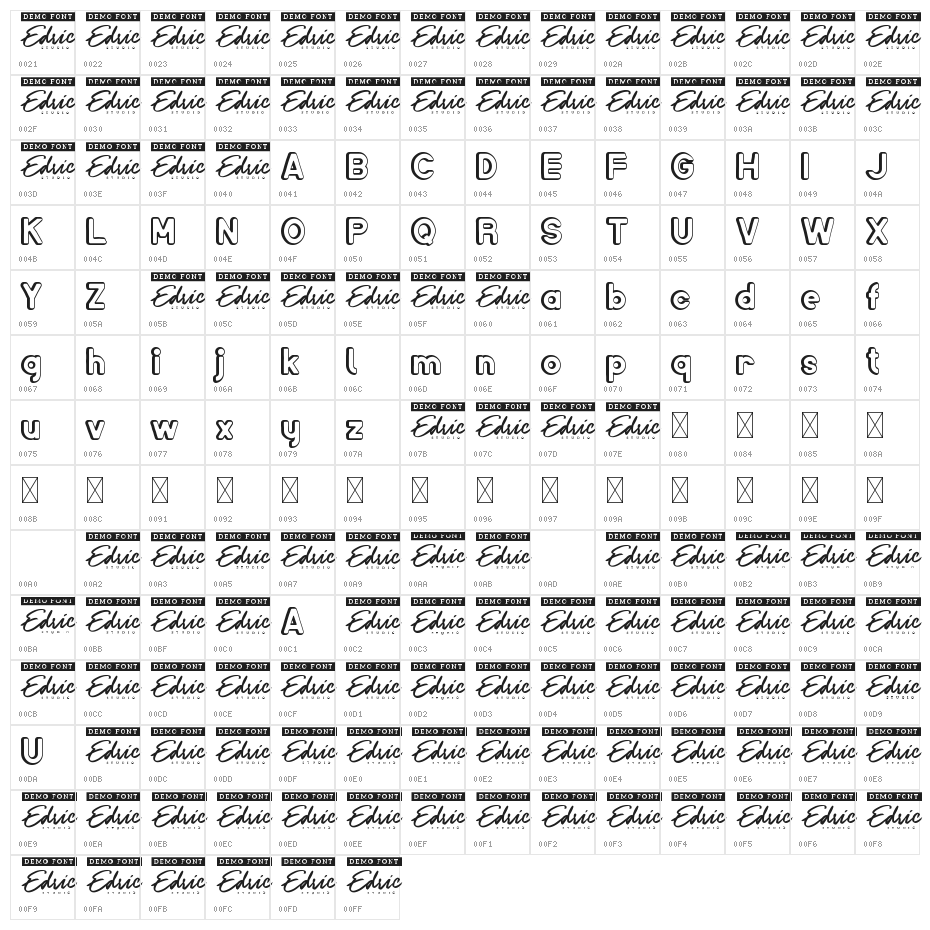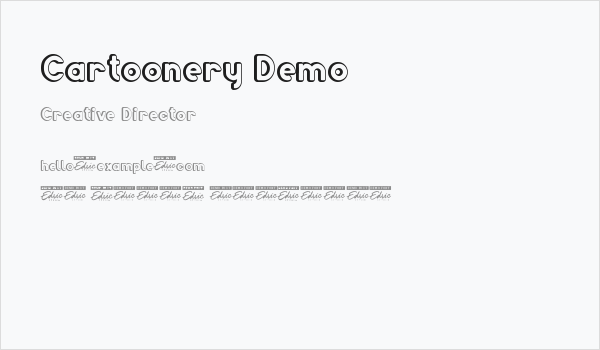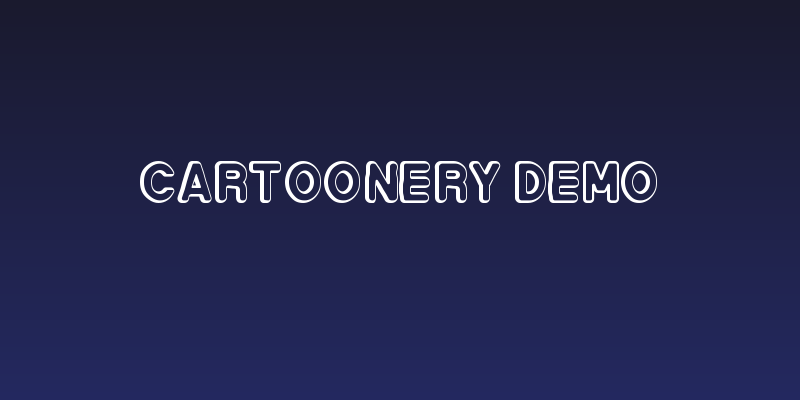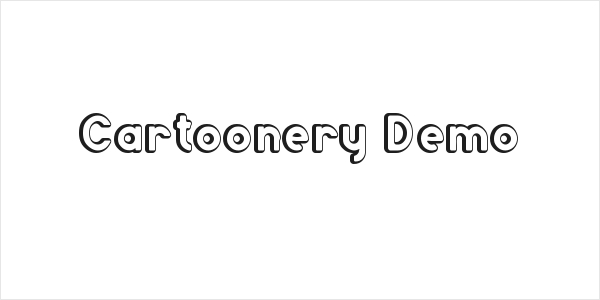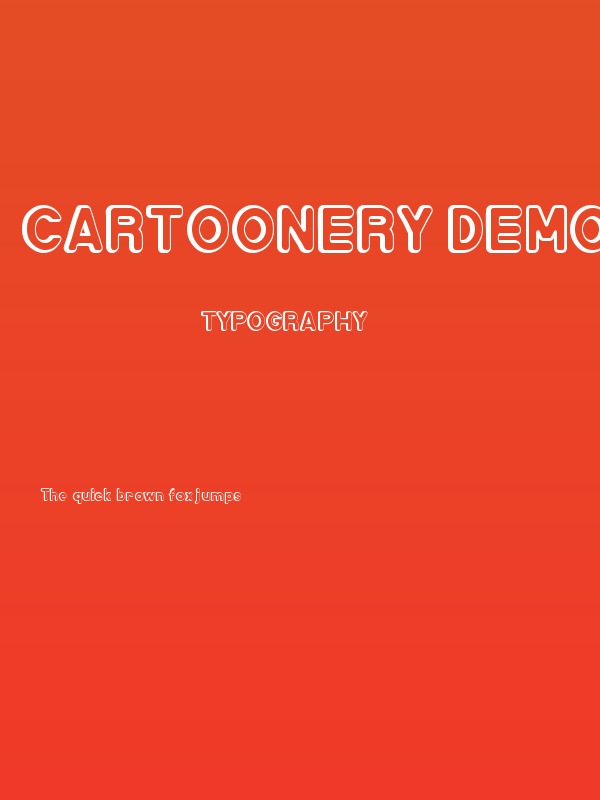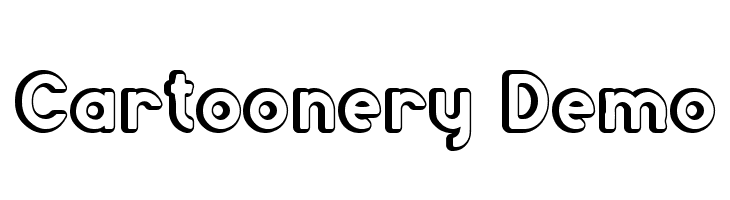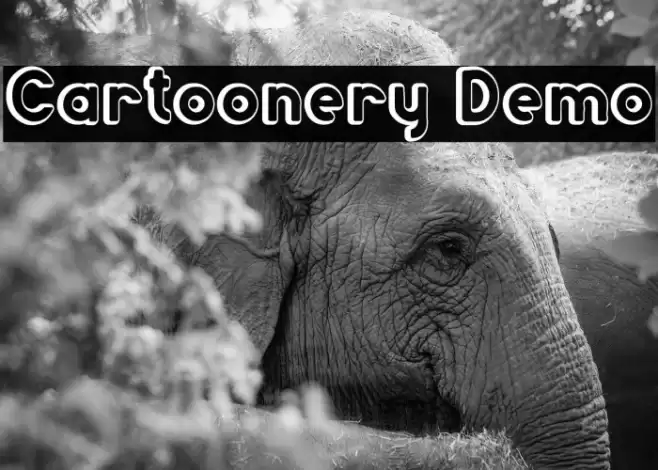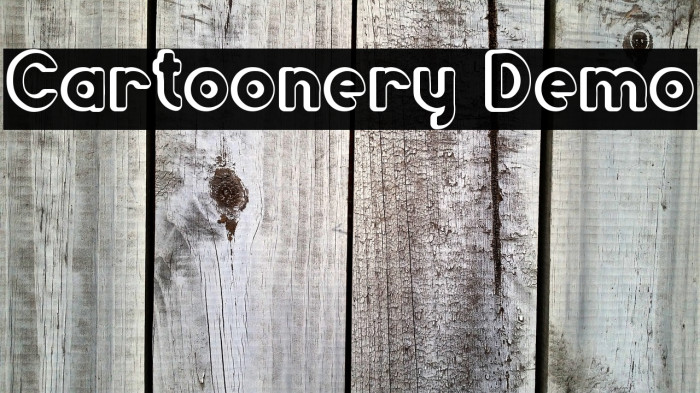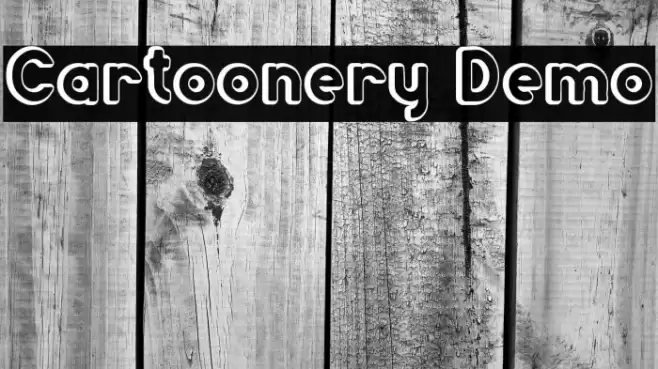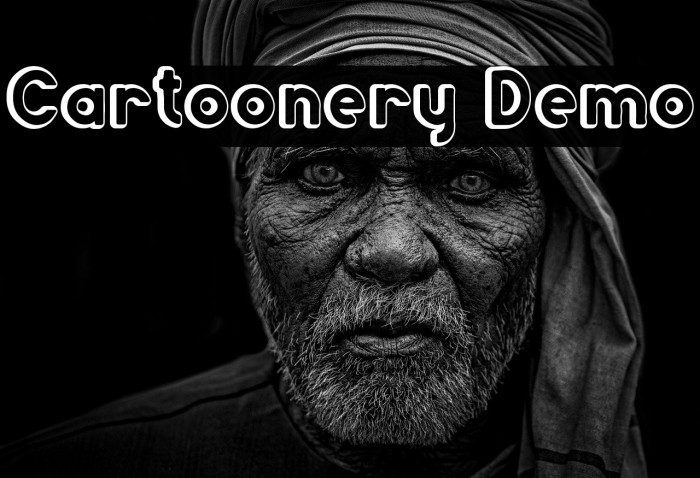
Cartoonery Demo Font
| Estilo general | Playful, Cartoonish |
| Proyectos propuestos | Ideal for children's books, comic strips, playful branding, and eye-catching posters. |